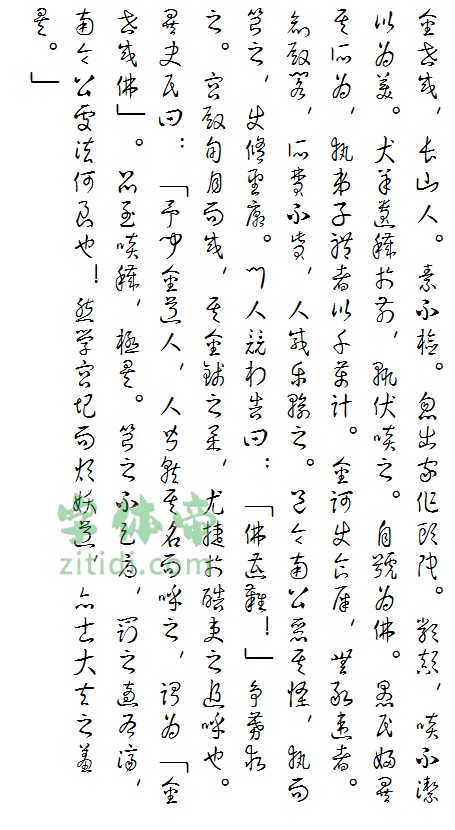
草书字体是百度贴吧一位大神mikhailcai自制的狂草字体。主要模仿孙过庭的字。因为他的字变化不多,容易规范。繁体,一共17000多个字,覆盖四书五经,四大名著和常见字。字体的作者在贴吧上表示这款字体免费使用,作者并放弃版权,大家可以随便使用。原版的字体只支持繁体中文(输入法裡设置繁体),后来网友@落霞孤鹜为了方便大家,制作了一个简入繁出的版本,即输入简体字也能正常输出繁体字。大家可以按需安装。在这里特别鸣谢@落霞孤鹜。
不过对于一简对多繁的情况不太好处理,如「钟」分别对应着「鐘」和「鍾」(最后取了「鈡」,与简体形近),「发」分别对应「發」和「髮」(取「發」,因为「发」字是「發」的草书楷化)等;其他在常用字范围内一对一的,取对应的繁体字(正体字),不改成形近字或该简体字所来源的异体字,如「钥」取「鑰」而不取「鈅」,「坝」取「壩」而不取「垻」,「铁」取「鐵」而不取「鉄」等。